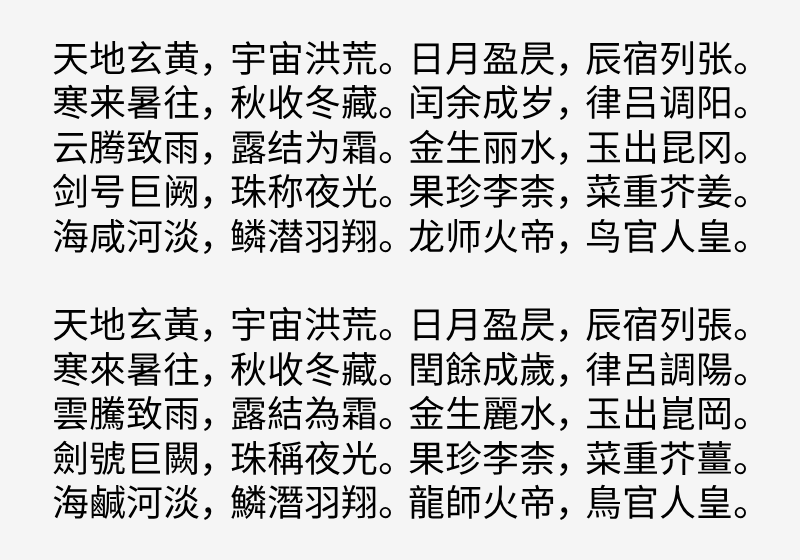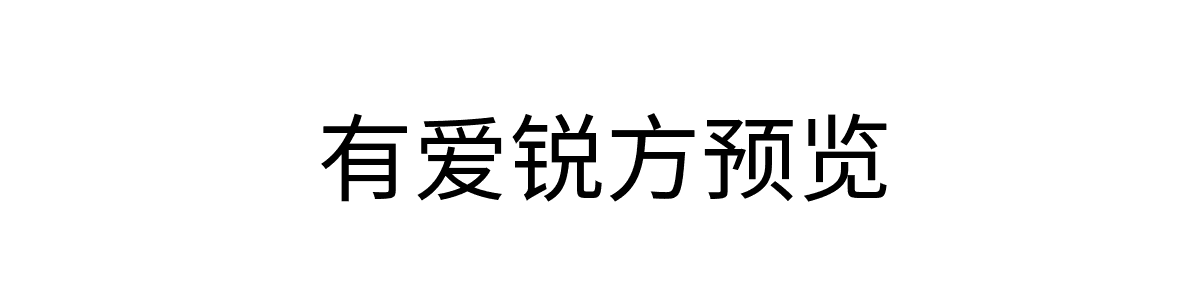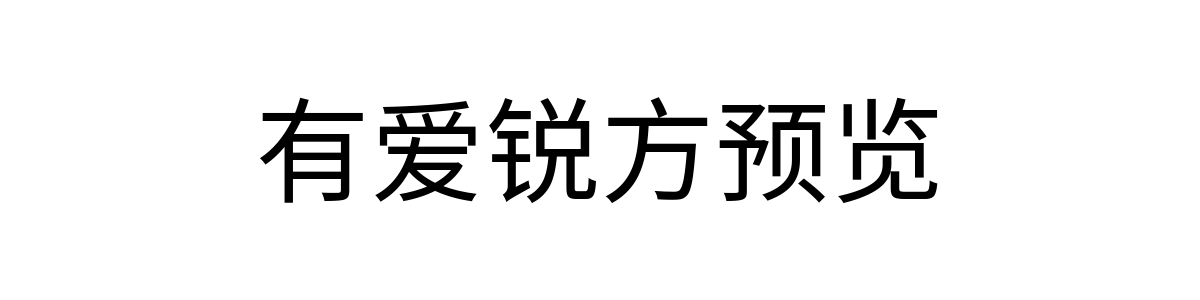
有爱锐方 2026年3月28日 上午11:18 • 多语言字体 • 阅读 602 目录 字体预览字体风格字体下载 有爱锐方(Nowar C²)是专门给《魔兽世界》和怀旧服做的一款游戏字体,能完整显示游戏里所有语言内容。它对字形做了专门优化,不管在什么分辨率下,文字显示都很清晰锐利,游戏界面里的字看着更清楚。 字体预览 有爱锐方 选择预设预览文本 选择预设文字 天地玄黄,宇宙洪荒。 雲騰致雨,露結為霜。 Hello, World 1234567890 !,、。!?:;“”‘’ A- A+ 自定义预览文本 选择字体字重 Light Regular Bold 字体风格 有爱锐方的重点就是边缘干净利落,通过专门调整,解决了屏幕上文字模糊、有毛边的问题。就算在战斗这种画面复杂、节奏快的场景里,字也很清楚,看信息一眼就能认出来。 没有多余花哨的设计,一切都是为了在游戏里更快、更准地看清文字。 字体下载 有爱锐方 下载次数 48 字体类型 黑体 授权协议 OFL 授权类型 免费商用 刷新 OFL日文简体繁体韩文黑体阅读字体 赞 (0) 0 0 生成海报 相关推荐 多语言字体 思源黑体 思源黑体(Source Han Sans / Noto Sans CJK)是 Adobe 与 Google 耗时三年联合打造的开源黑体,于 2014 年 7 月正式发布,也是业内首个真正覆盖全 CJK 区域的通用字体。这款字体支持简繁中文、日文、韩文,搭配完整的拉丁字符集,单字体字符量超 65000 个,全家族字形总数接近 50 万,是目前字库最完整、应用最广泛的免费商用字体之一。 2026年3月27日 7.1K5 多语言字体 有爱圆体 有爱圆体(Nowar Rounded)是专门为《魔兽世界》和经典怀旧服制作的游戏界面字体。它由 Noto Sans 和资源圆体(Source Han Rounded)结合衍生而来,既保留了思源黑体规整易读的结构,也延续了资源圆体柔和圆润的字形特点。 2026年3月29日 8320 多语言字体 有爱黑体 有爱黑体(Nowar Sans)是面向《魔兽世界》与怀旧服制作的开源内嵌字体,由 Noto Sans 与思源黑体整合而成。这款字体针对游戏界面做了专门适配,不管是任务描述还是物品说明,都能完整、准确地显示,同时也考虑到了玩家长时间游戏容易产生视觉疲劳的问题,在阅读体验上做了优化。 2026年3月29日 4850 多语言字体 更纱黑体 更纱黑体(Sarasa Gothic)是一款面向中日韩与英文混排场景深度优化的开源免费字体,以 100% 缩放下极佳的屏幕显示效果和可读性为亮点。它由西文优质字体 Inter、编程等宽字体 Iosevka ,搭配思源黑体的 CJK 部分整合而成。 2026年4月3日 1.3K1 多语言字体 思源等宽 思源等宽(Source Han Mono)是 Adobe 发布的开源等宽字体,属于思源黑体系列里专门面向编程使用的版本,主要用来统一中日韩文字在代码里的显示效果。思源等宽整体风格简洁、规整、中性,无多余装饰,等宽特性稳定,中英文、符号排版统一,清晰易读,长期使用不易疲劳,非常适合代码编辑、终端、IDE 等专业场景。 2026年3月17日 8290 发表回复 请登录后评论...登录后才能评论 提交